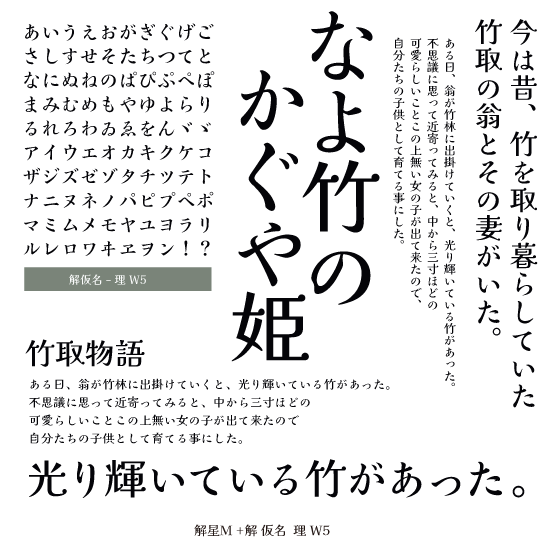
●仮名のみの使用はできますが、一般にはアドビー系アプリケーションなどで、他のフォントと合成して使われます。●両仮名と約物など約400字を収録です。ぁあぃいぅうぇえぉおかがきぎくぐけげこごさざしじすずせぜそぞただちぢっつづてでとどなにぬねのはばぱひびぴふぶぷへべぺほぼぽまみむめもゃやゅゆょよらりるれろゎわゐゑをんァアィイゥウェエォオカガキギクグケゲコゴサザシジスズセゼソゾタダチヂッツヅテデトドナニヌネノハバパヒビピフブプヘベペホボポマミムメモャヤュユョヨラリルレロヮワヰヱヲンヴヵヶ、。ヽヾゝゞ〃々〆ー外約物。●OpenType アウトライン抽出可、PDFでの埋込可能です。アプリケーションがOpenTypeに対応していない場合には使用できません。Macintosh 、Windowsどちらでも使用できます。
解仮名- 理 Set-Kaisei
◉ Google Fonts Kaiseiの各Weightに対応した仮名フォントの紹介です。(W4=Regular,W5=Medium,W7=Bold,W8=ExtraBold) 合成フォントとして使用可能です。
Kaisei(解星)はhttps://fonts.google.com/?query=Font-Kaiからダウンロードできます。◉ 「仮名-理」は整然としたフォルムですが決して硬くはありません。穏やかで安心出来る表情です。どんなシーンでも幅広く使えることと思います。書籍本文など使用を考慮して明解な視認性を大切にしました。